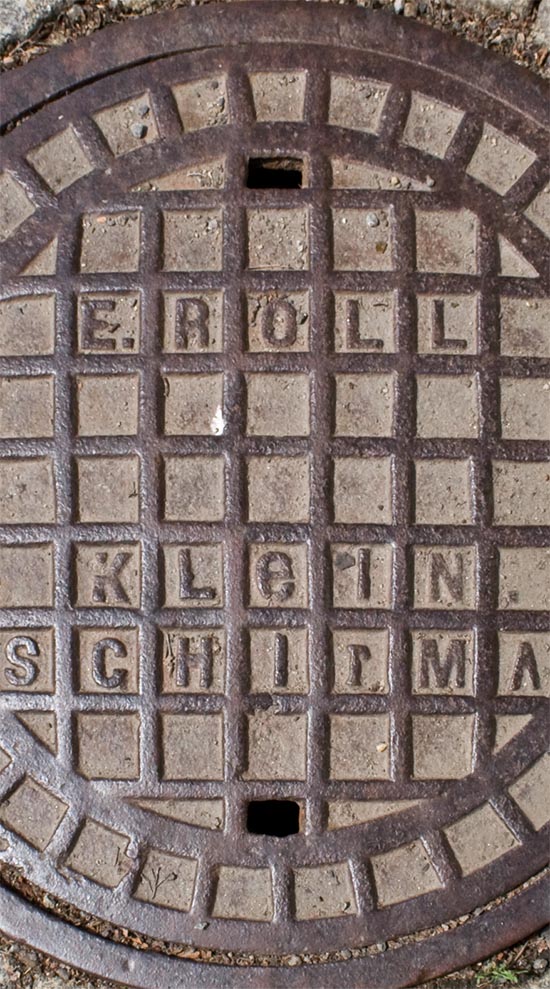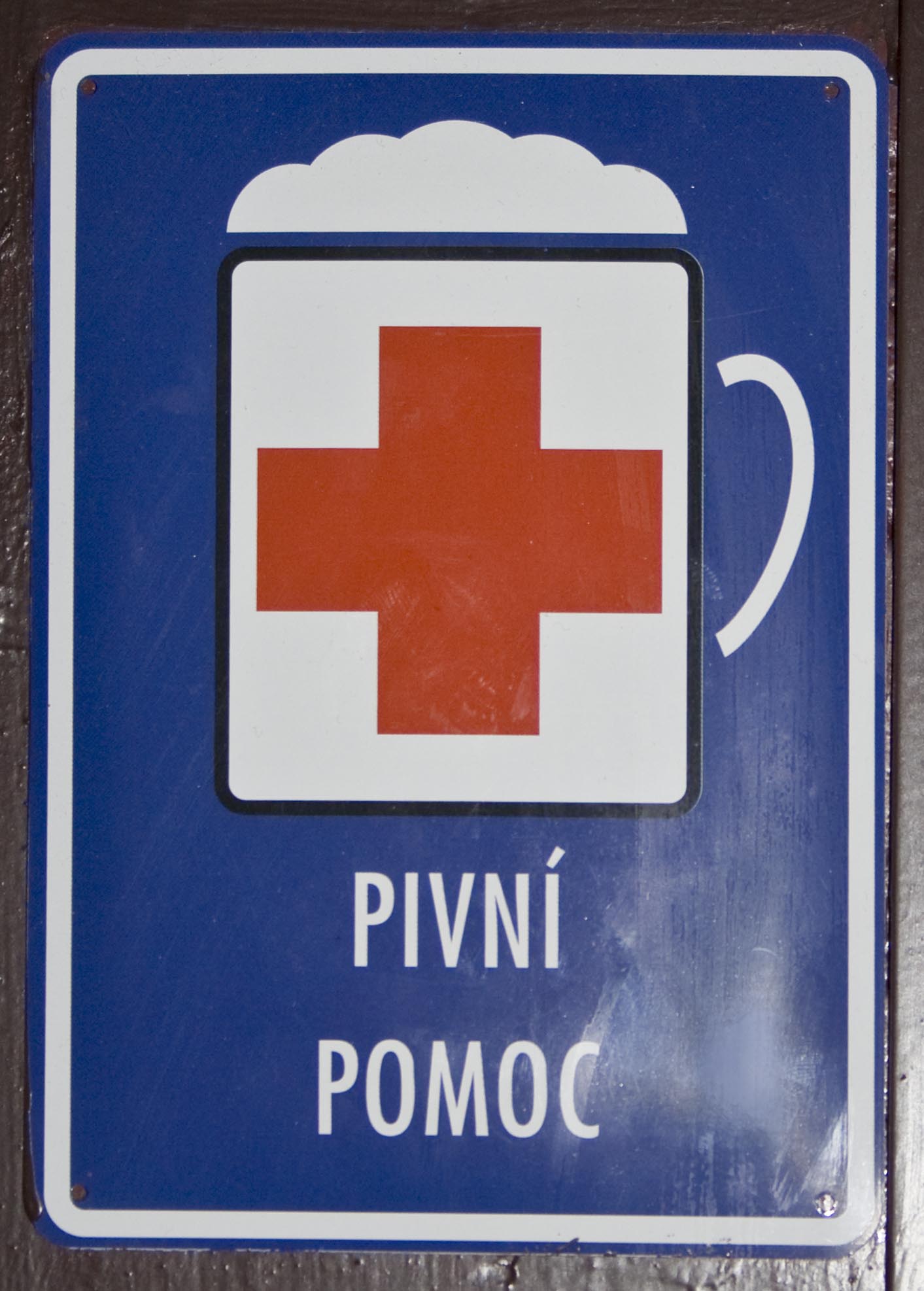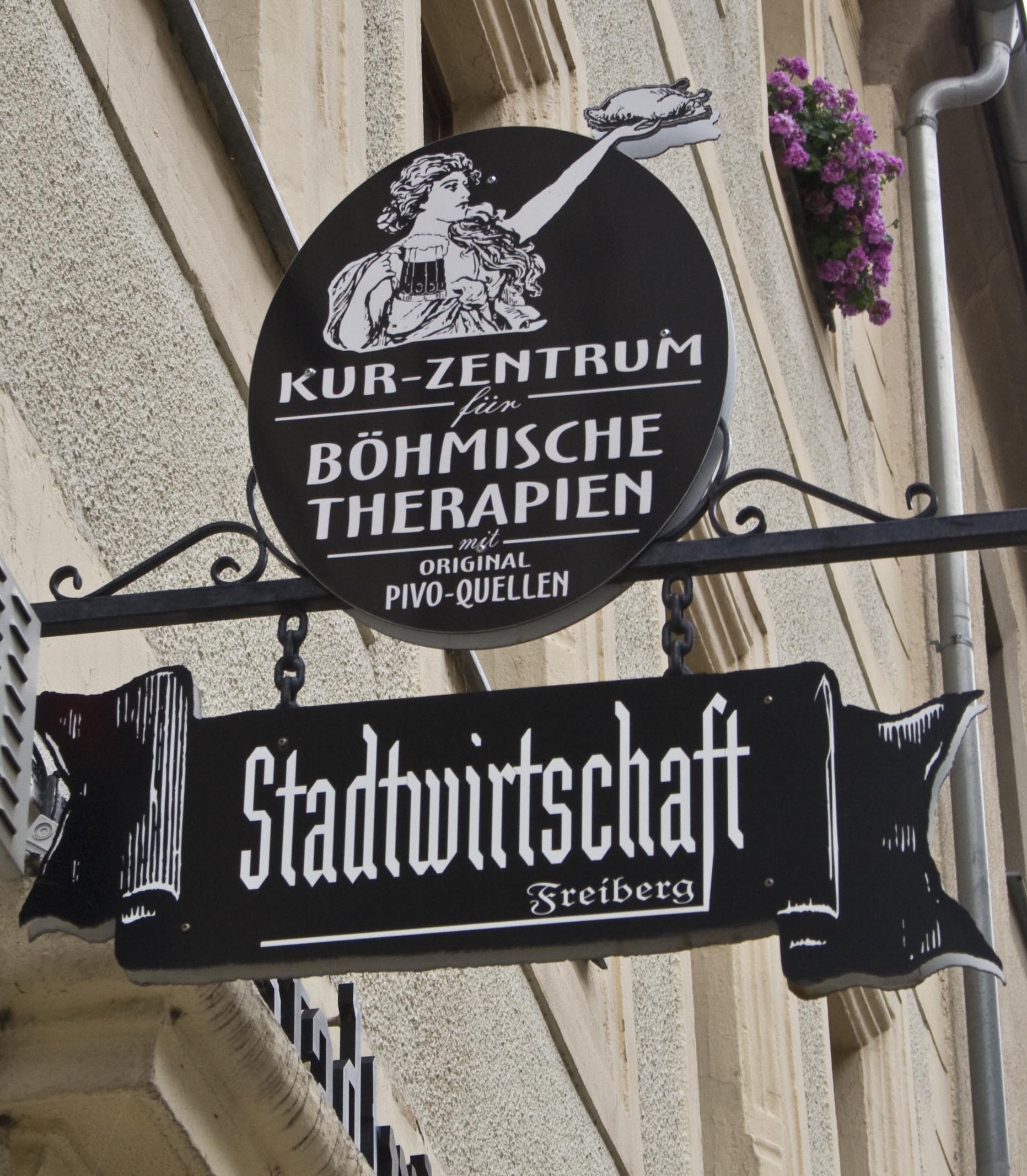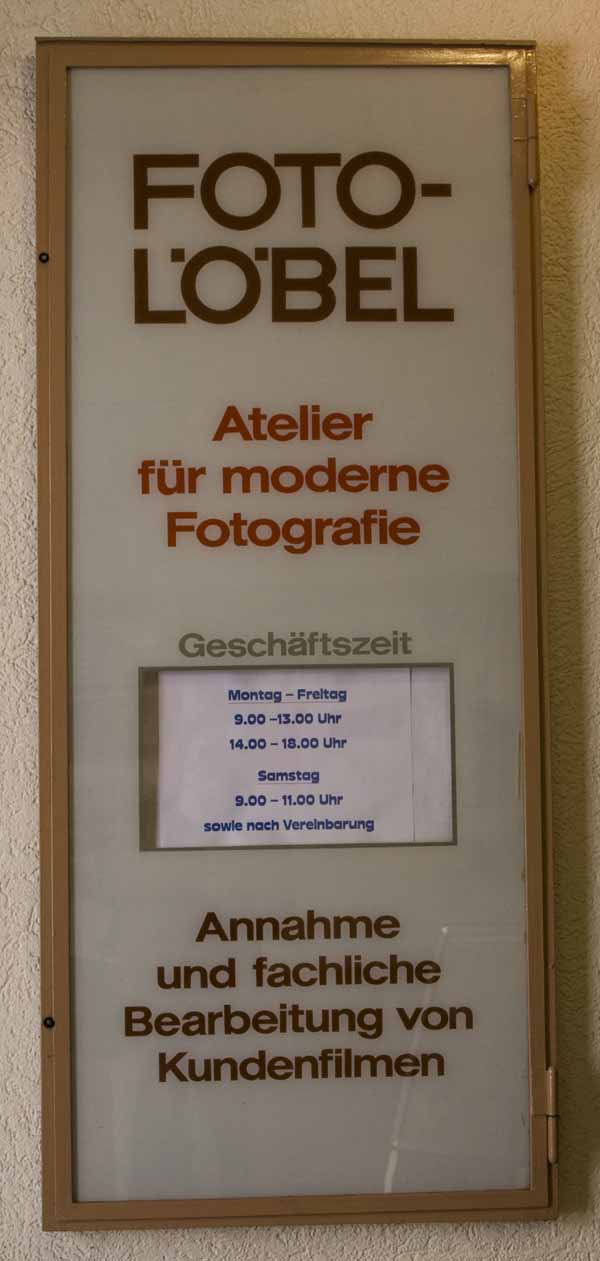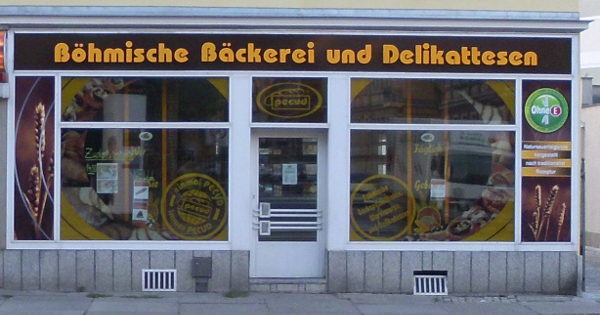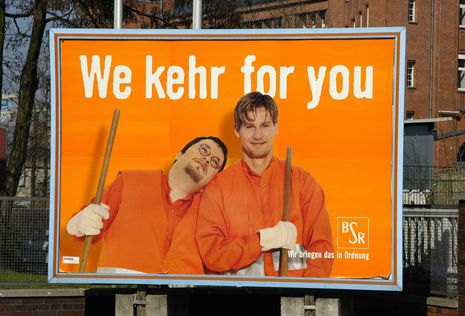
Übrigens sammelt auch Wigald Boning Einkaufszettel, eine kleine Auswahl hat die Süddeutsche seinem Buch entnommen
Hafenstadt halt. :-? Da kommen doch sicher Schiffe aus aller Welt. Da kann man sich das schon vorstellen.
Tse, das war doch bloß ein kleines Fundstück, unfreiwillig komisch in der Formulierung. Ich wollte Euch lediglich einen kleinen Schmunzler entlocken – schließlich ist es endlich mal wieder richtig Sommer – und ich für meinen Teil freue mich drüber!  ;-)
Hafenstadt halt. :-? Da kommen doch sicher Schiffe aus aller Welt. …
Die meisten davon aus Bayern, klar.  :schonklar:
Nee, im Ernst: "Neger" ist in Bayern wirklich ein gängiger und völlig unaufgeladener Begriff. Drum wäre mir als altem Bayern das noch nicht mal aufgefallen :-)
Nee, im Ernst: "Neger" ist in Bayern wirklich ein […] völlig unaufgeladener Begriff.
Das haben weiße US-Südstaatler über den Gebrauch von »Nigger« in ihrer Region auch lange behauptet. Das Problem ist in beiden Fällen, dass weder du noch sie die Deutungshoheit haben (es sei denn, dein Avatar ist irreführend und dein tatsächliches Aussehen legt eine Herkunft aus dem Afrika südlich der Sahara nah).
Hey, das ist so politisch inkorrekt wie letzt die Filets vom weiblichen Hahn politisch korrekt waren und generiert so seinen Humor.
Apropos ...
Ein "Radiofundstück" von vorhin ...
Der Spruch des wohl gestrigen Fernsehkommentators "Wir sind Europameisterin" veranlasste den SWR3-Moderator, paar Sätze "korrekt" zu gendern, was damit endete, dass er einen schönen Empfang der Spielerinnen auf der Frankfurter Römerin erwartete ...
... und es kam wie es kommen musste:
Den find ich durchaus witzig, die haben auch immer so lustige T-Shirts beim CSD an (unter anderem obigen Spruch oder der Aufdruck "Nein, das ist kein Kostüm").
Oh weh, da fällt die Einschätzung schwer, ob unser geschätzter Leipziger Kollege sich darüber freut oder eher ärgert. C-Schreibweise versus noch älterer Name:
Wegen der typographischen … äh … sagen wir mal: Besonderheiten von »KLeIN.SCHIrMΛ« — ausnahmsweise nicht im Drainspotterstrang, sondern hier:
Nun ja. Falls diese Böhmische Bäckerei auch von einem böhmischen Schriftschnitzer bedient wurde, gäbe das mildernde Umstände.
Man kann natürlich besser böhmisch werben, wie die »Stadtwirtschaft Freiberg« zeigt, die ein schön ausgebautes Werbekonzept hat, das weit besser ist, als das breitgeklopfte Wort »Freiberg« vermuten läßt.
(Kann man in etwa mit »bierliche Hilfe« übersetzen.)
Immerhin: Bauhaus Heavy
Man wollte halt durch Weglassen des h nicht sofort kundtun, dass es hier zu den Brötchen paar delikate Thesen über die Dorfbevölkerung kostenlos dazu gibt ... ;-)